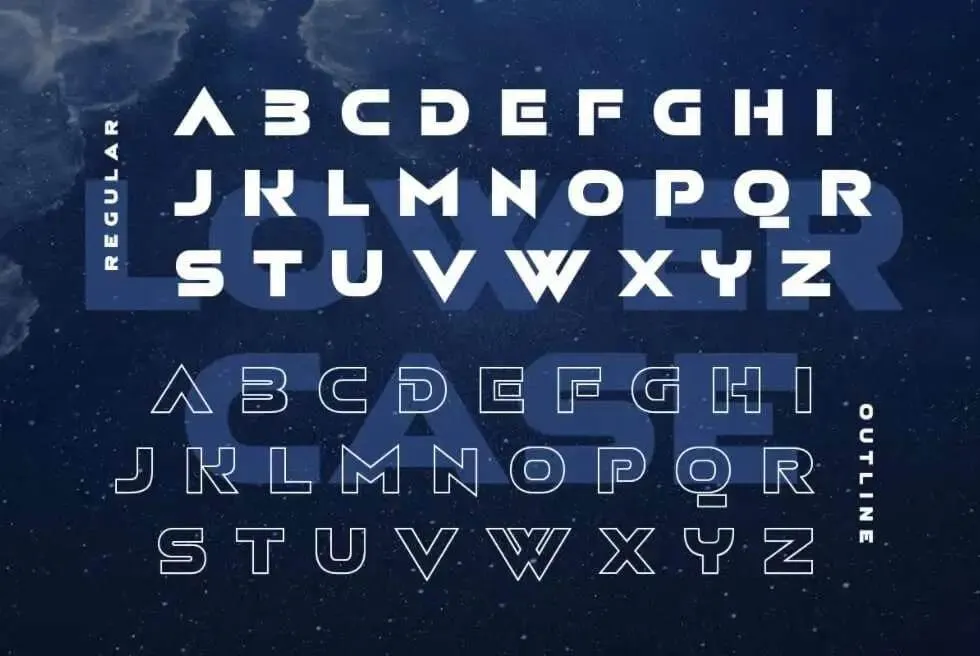
Font Aerospace là một phông chữ Khoa học viễn tưởng hiện đại được tạo ra đặc biệt cho các nhu cầu về kiểu chữ Công nghệ, Khoa học viễn tưởng, hiện đại và nổi bật hơn, với các phong cách thay thế bổ sung giúp thiết kế của bạn trở nên đáng nhớ hơn.
Thật hoàn hảo để thêm tổng quan về phong cách và tiêu đề của bạn cho tương lai, công nghệ, hành động và chủ đề công nghệ. Và đặc biệt đối với phông chữ này, chúng tôi đã tạo ra phong cách hành động táo bạo và cảm giác hiện đại, vì vậy hãy tận hưởng để tạo bất kỳ dự án nào sẽ thể hiện ý tưởng chính của bạn.
Font Aerospace với:
• Các ký tự biến thể Phông chữ hiện đại đã sẵn sàng để sáng tạo
• Sẵn sàng với tất cả các ký tự chữ hoa